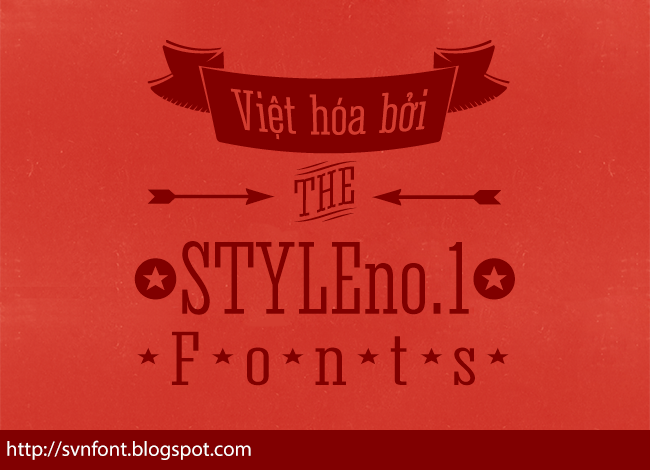
Corki một typeface tuscan đơn giản mà đẹp, gồm có 4 kiểu: regular, tuscan, rounded và tuscan rounded. Font hỗ trợ cả chữ in hoa và in thường (so với phiên bản cũ trước đó). Ngoài ra, font cũng được chỉnh sửa và cải thiện một số chi tiết như ký tự “K”, bộ chữ số, cũng như độ dày của các serif. Font rất thích hợp với thiết kế về chủ đề giáng sinh, tiêu đề, nhãn hiệu, logo, bạnner,…
Nhà thiết kế: Alexander Nedelev
Nhà phát hành: Typedepot
Kiểu: Regular, Tuscan, Rounded, Tuscan Rounded